Wortzwischenraum
Typografischer Terminus für den nichtgedruckten Teil bzw. Leerraum zwischen zwei Wörtern; auch als Wortabstand, im materiellen Schriftsatz mit physischen Drucktypen aus Metall (z.B. aus einer Blei-Zinn-Antimon-Kupfer-Legierung) als »Ausschluss« (Ausschluß), in der Informationstechnologie (IT) und im Webdesign als »word-spacing« bezeichnet; fspz. Abk. »WZ«. 1)
Die Erweiterung von Wortzwischenräumen innerhalb einer oder mehrere zusammenhängender Zeilen innerhalb einer Kolumne wird als »Austreiben« oder »Ausbringen« bezeichnet, das gleichmäßige Ausgleichen von Wortzwischenräumen innerhalb einer festgelegten Satzbreite als »Ausschließen«.
Die Ausmaße und der Rhythmus von Wortzwischenräumen nehmen unmittelbar Einfluss auf den Grauwert eines Schriftsatzes. Ein idealer, möglichst harmonischer Wortzwischenraum fördert die Lesbarkeit.
Die Evaluierung von Wortzwischenräumen gehört in das Segment der Schriftgestaltung (z.B. Bemaßung von Leerräumen und Kerningtabellen) und der Mikrotypografie (z.B. Abstimmung von NSW und OSW).
Die Bemaßung von Wortzwischenräumen in der Normalschriftweite (NSW) entsteht im Electronic Publishing einerseits durch das vorgegebene Wortabstandskerning der genutzten Fonts, andererseits durch individuelle Einstellungen und Eingaben in den Schriftsatzprogrammen, beispielsweise für den Optischen Schriftweitenausgleich (OSW) in InDesign® von Adobe® oder in QuarkXpress® von Quark®.
Wortzwischenräume werden im DTP Desktop Publishing in der Regel in der relativen Maßeinheit »Geviert« bemessen. Im Web Publishing wird das Abstandsverhalten zwischen Tags und Wörtern mit der Stylesheet Eigenschaft (CSS3) 2) »word-spacing« in unterschiedlichen Maßeinheiten (z.B. px, em, %) beschrieben, wobei die Browser-Kompatibilität zurzeit noch nicht konsistent ist, d.h., die Wortzwischenräume fallen in jedem Browser (z.B. Safari® von Apple® oder Google Chrome® von Google®) unterschiedlich groß aus.
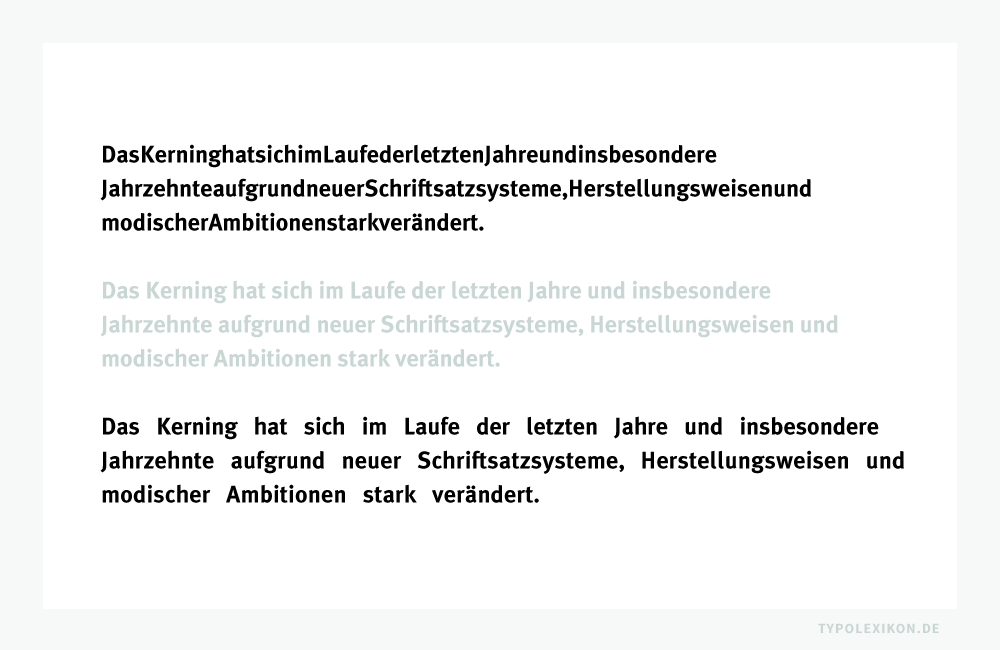
Sowohl das Zeichenabstands- als auch das Wortabstandskerning hat sich im Laufe der letzten Jahre und insbesondere Jahrzehnte aufgrund neuer Schriftsatzsysteme, Herstellungsweisen und modischer Ambitionen stark verändert. Das relative Kerning unterscheiden sich deshalb je nach Schrift, Schriftsatzsystem, Schriftgestalter:in, Type Foundry und Erscheinungsjahr. 3)
Wortzwischenräume sollten deshalb grundsätzlich bei jeder Schrift und bei jeder Schriftsatzarbeit individuell beurteilt werden. Automatische Vorgaben durch Fonts und Software sind in der Regel nicht ausreichend, um zufriedenstellende Ergebnisse zu erzielen. Standardeinstellungen, beispielsweise bei Adobe InDesign® CC 2020 unter »Voreinstellungen → Absatzformatoptionen → Abstände → Wortabstand (Minimal bis Maximal)« sollten grundsätzlich immer auf die jeweilige Schrift, den Satzspiegel bzw. den Gestaltungsraster abgestimmt werden.
Wortzwischenräume im Blocksatz
Ein »tadelloser Ausschluss« 4) – also ein durchgehend annähernd gleichmäßiger Wortzwischenraum – vermeidet Gießbäche und zählt zu den Qualitätsmerkmalen eines Blocksatzes. 5)
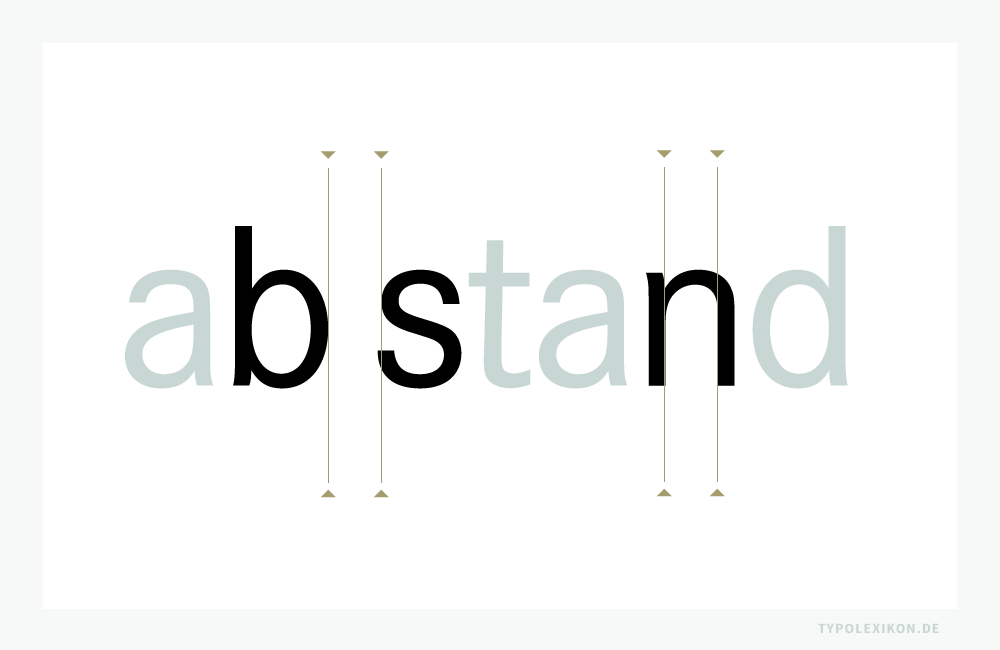
Mit der Einführung der Englischen Typografie (Antiqua-Schriften) in den 1940er Jahren in Deutschland und Österreich, gilt im Segment der Lesetypografie im Blocksatz bei Lesegrößen als Standardmaß für einen Wortzwischenraum »ein Drittel des Schriftgrads« oder die »Punze (Binnenraum) der Minuskel ›n‹«, unabhängig davon, ob eine Schrift Serifen hat oder nicht.
Um beim Blocksatz die Zeilenlängen zu erhalten, müssen Wortabstände vergrößert oder verkleinert werden. Diese sollten aber oben genannte Werte niemals um mehr als die Hälfte unterschreiten und um nicht mehr als das Doppelte überschreiten, da sich dies auf die Schriftsatzästhetik und den Leseprozess (siehe auch Fixationen) negativ auswirkt und darüber hinaus lesehemmende Gießbäche entstehen.
Wortzwischenräume im Flattersatz
Da Flattersatzarten keine einheitlichen Zeilenlängen besitzen, entfällt die Notwendigkeit, die Wortzwischenräume zu vergrößern oder zu verkleinern. Hier gilt als feste Wortabstandsgröße der Binnenraum der Minuskel »n«.
Wortzwischenräume im Majuskelsatz
Majuskeln und Kapitälchen werden in der gepflegten Typografie im Versalsatz grundsätzlich immer etwas – ausgehend von der Normalschriftweite – spationiert. Das bedeutet in der Regel, dass auch die Wortzwischenräume proportional erweitert werden, was wiederum bedeutet, dass diese dann oftmals zu groß wirken. In diesem Falle sollten die Wortzwischenräume dann im Sinne des Optischen Schriftweitenausgleichs unterschnitten bzw. ausgeglichen werden. Gleiches gilt für den Sperrsatz.
Wortzwischenraum und Schriftgrad
Wie bei Schriftlaufweiten, empfiehlt es sich, die Wortzwischenräume auf die gewählten Schriftgrade abzustimmen. Generell gilt die Faustregel »je größer ein Schriftgrad, desto geringer der Wortzwischenraum«. Oder anders formuliert: Konsultationsgrößen, Lesegrößen, Ferngrößen und Schaugrößen benötigen unterschiedlich große Wortabstände.
Wortzwischenraum und Schriftweite